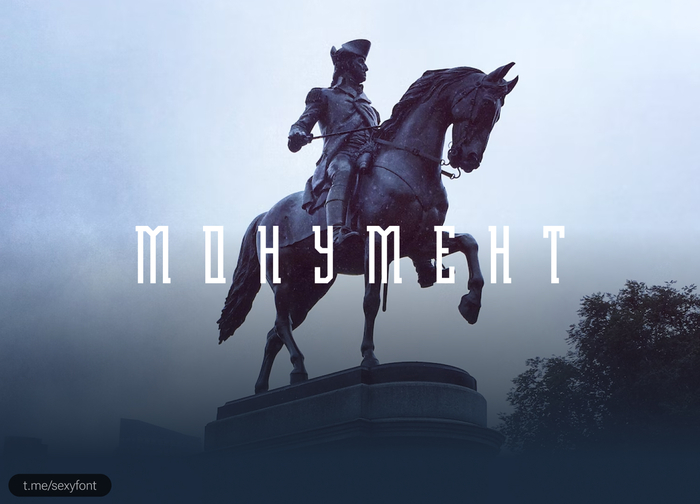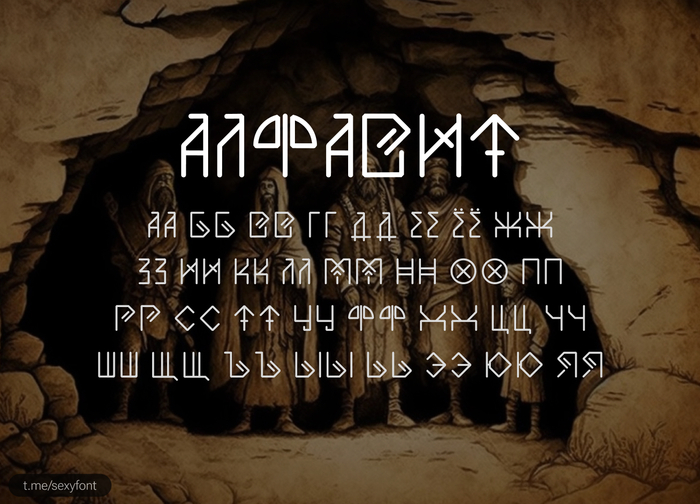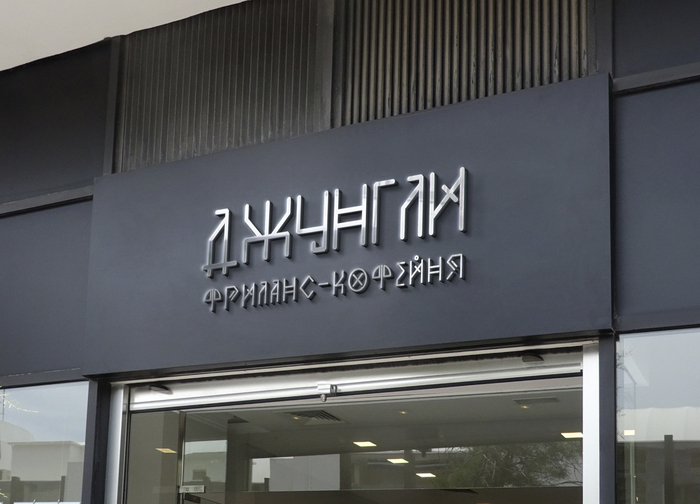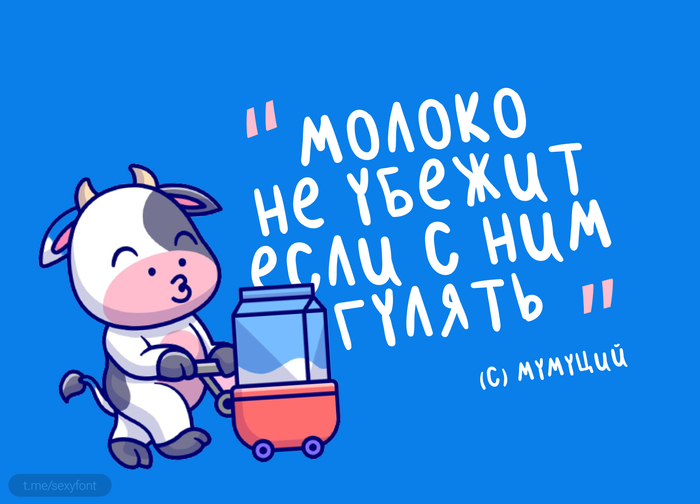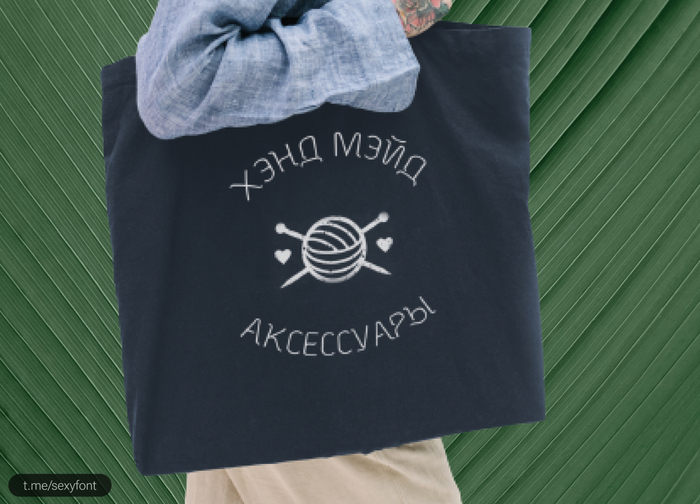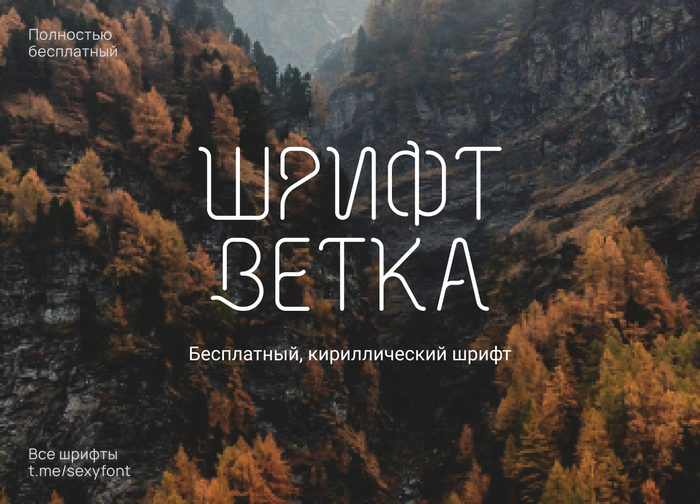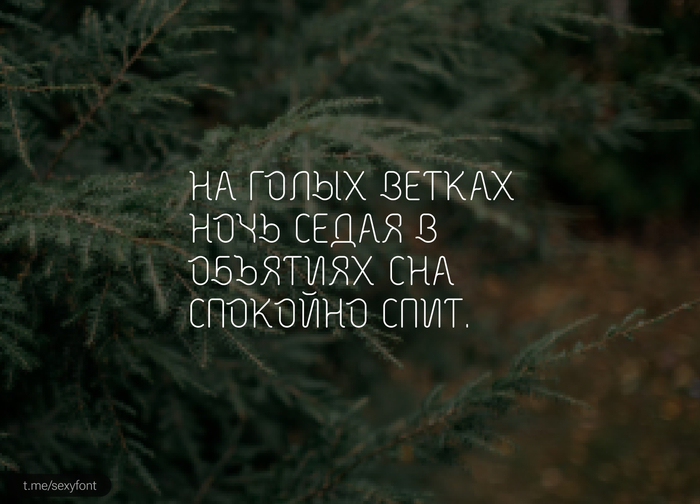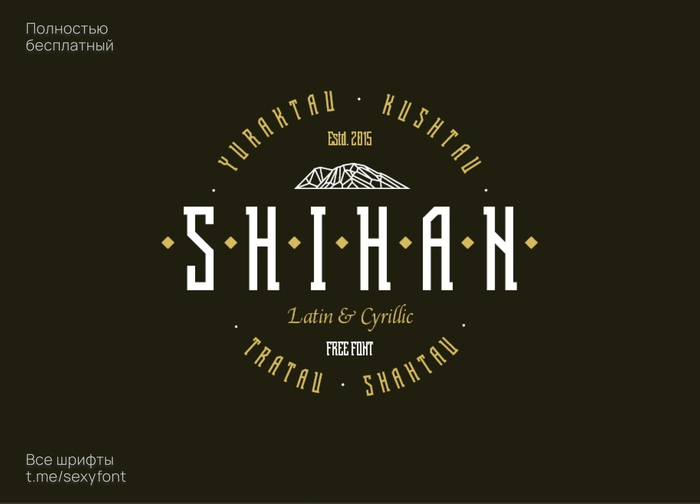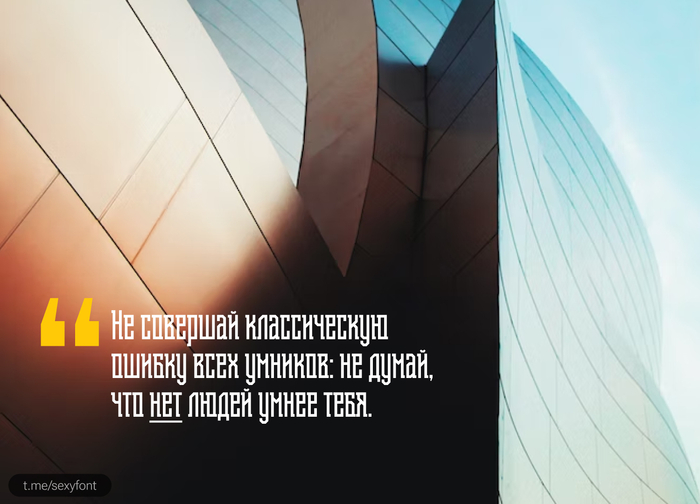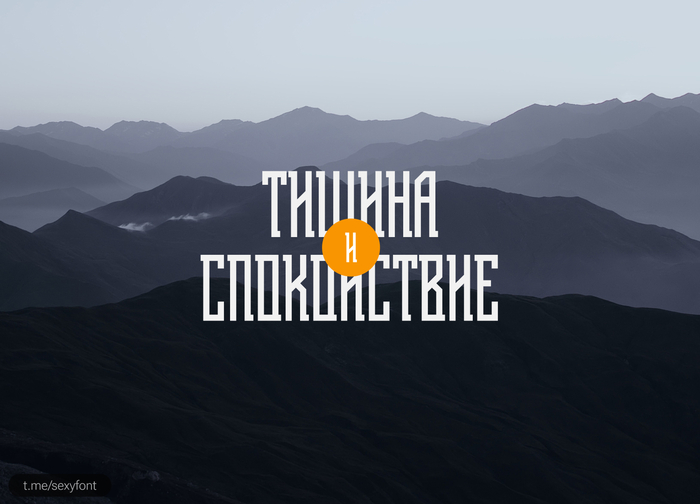
Шрифт "злые птички"
Шрифт «Злые птички». Помните такую игру?) Оказывается есть адаптированный шрифт на кириллице. Но чет мне кажется они свистнули этот шрифт из «ну погоди» Най-най-нананнаана
С его помощью вы можете создавать макеты, которые будут "расти" на глазах у ваших пользователей и клиентов, словно ветки на дереве. А если вы решите использовать его в логотипе, то ваш бизнес точно "взойдет" на новые высоты, как "высокая берёзка"!
Молоко. Бесплатный, округлый шрифт для твоих проектов. Если вы ищете способ сделать свой текст более кремовым и гладким, то этот шрифт - именно то, что вам нужно. Но будьте осторожны, использование этого шрифта может вызвать желание выпить больше молока, чем вы можете переварить!
Уууу. Тумба-юмба. Скоро коллекцию и отдельную категорию можно будет открывать под эти шрифты. Да, плохо, читаемые, но зато очень необычные) Riimut — это акцидентный шрифт, вдохновленный финно-угорской мифологией.
Гарнитура содержит набор символов латинского и кириллического алфавита.
Шрифт Шихан. Назван в честь горы, на которой я был кстати)
От автора: Бесплатный шрифт, вдохновленный башкирскими геометрическими орнаментами. Это БЕСПЛАТНЫЙ шрифт, и его разрешено использовать в коммерческих целях. Шихан поставляется в формате OpenType и поддерживает базовую латиницу, кириллицу и башкирский язык. Это акцидентный шрифт, для сохранения читаемости лучше использовать в коротких заголовках. Автор: Sergei Godovalov
Саквояж. Необычный шрифт в ретро-стиле. От шрифта веет приятной стариной) Автор: maxim keshishev. Бесплатно для всего.
Катя-Катя-Екатерина. Очень красивый рукописный шрифт. Не идеально, но хорошо проработанные отступы между буквами, что редкость для этой стилистики. Автор кириллизации: А. Л. Гофманн. Кириллическая версия бесплатна для личного и коммерческого использования. По латинской не скажу) Шрифт, которым даже материться можно красиво. Презентация от нас.
Tetra. Необычный кириллический шрифт. По сути это 2 шрифта: Тетра и тетра декоративный. Оба по-разному выглядит в зависимости от строчных или прописных букв. Лайкос автору за старания. Шрифт полностью бесплатный для личного и коммерции. Автор: Alex Frukta